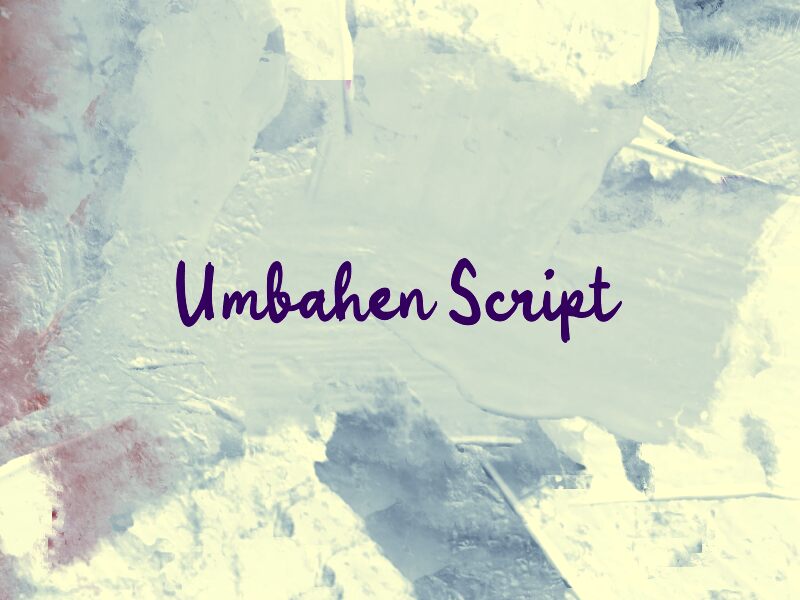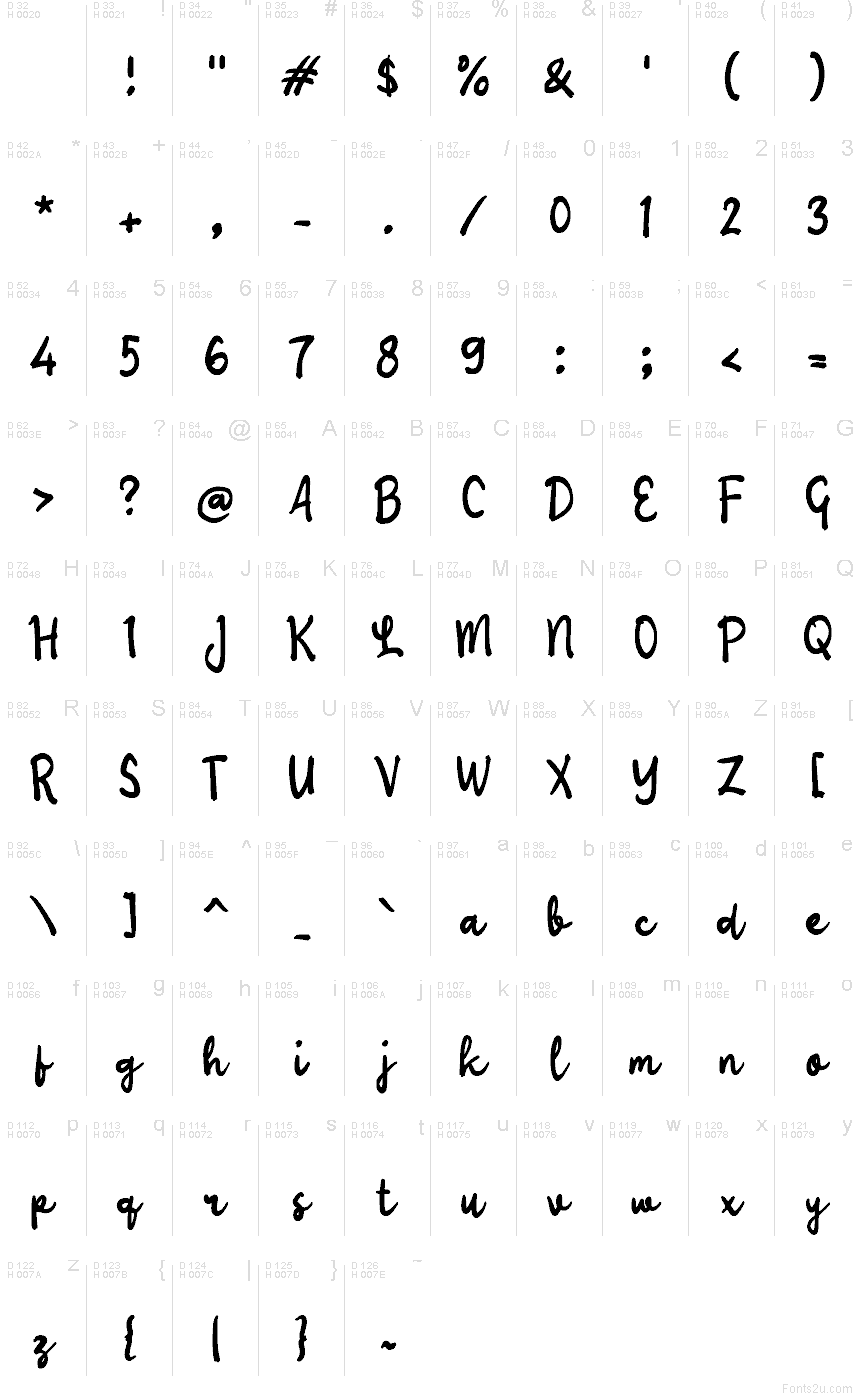
Umbahen Script
Umbahen Script от Wep — это бесплатный рукописный шрифт с ритмом свободной кисти и игривым, пружинистым начертанием. Буквы выглядят нарисованными от руки: толстые штрихи, округлые соединения и высокие петли придают тексту легкий и живой характер.
Он идеально подходит для брендинга кафе, упаковки косметики, поздравительных открыток, постов в соцсетях и повседневных плакатов, где бесплатный шрифт должен создавать ощущение тепла и личной подписи, избегая излишней формальности. Используйте его в коротких заголовках, обложках, табличках или простых логотипах, когда хотите, чтобы петли строчных букв и фактура кисти говорили сами за себя.